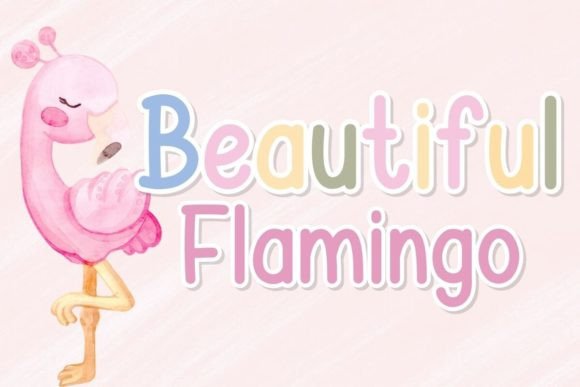
Beautiful Flamingo
適切なデザイン要素を見つけるのは難しい場合がありますが、Beautiful Flamingoは作品を即座に引き立てる優れたコレクションを提供します。
POD(オンデマンド印刷)製品、結婚式の招待状、またはソーシャルメディアのグラフィックを作成している場合でも、Beautiful Flamingoは理想的です。